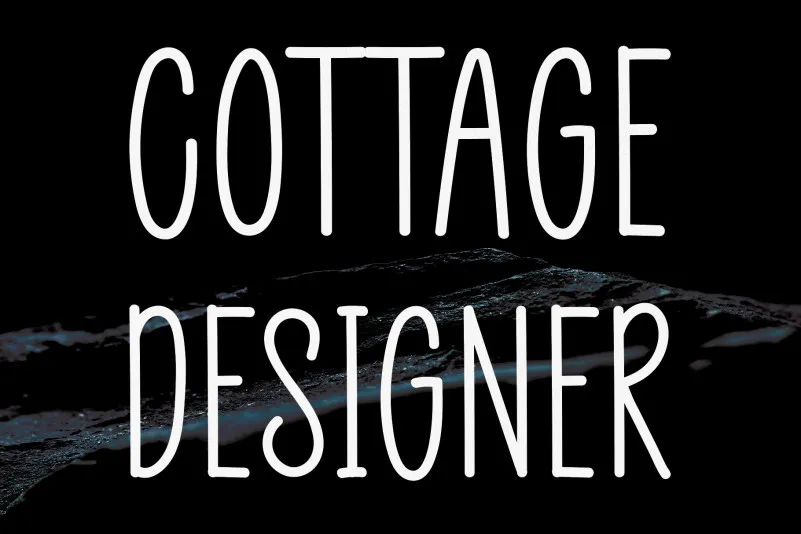
Cottage Designer Handwritten Font – Download Grátis
A Cottage Designer Handwritten Font é uma opção perfeita para quem busca uma mistura elegante entre a simplicidade do script e a delicadeza do traço manual. Com suas linhas limpas, altas e delgadas, essa fonte transmite uma sensação de formalismo suave junto com um toque de informalidade natural, tornando-a perfeitamente adaptável para qualquer design formal ou não formal que você goste de criar. Ideal tanto para uso em materiais informativos quanto gráficos decorativos e interativos, a Cottage Designer Handwritten Font garante uma identidade visual sólida e única. Ela é perfeita para aplicação em sites, logotipos, embalagens de produtos ou qualquer outro projeto que valoriza um toque delicado e pessoal. Composta por linhas suaves e traços finos, esta fonte oferece uma variedade rica de tamanhos e tipografias, garantindo a sua utilidade em diversas situações.